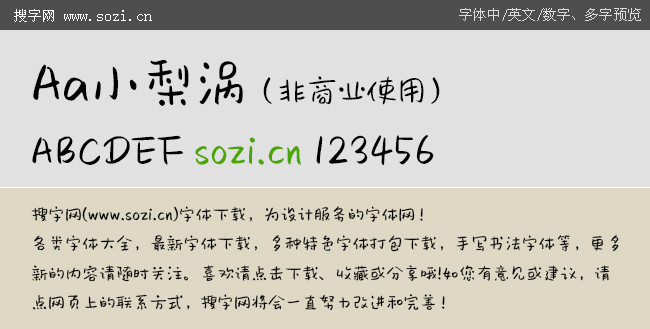
Aa小梨渦(非商業(yè)使用)
搜字網(wǎng)給大家提供一款A(yù)a小梨渦(非商業(yè)使用)中文字體下載,該字體是一款手寫風(fēng)格的卡通字體,充滿童趣,適合包裝畫冊(cè)等兒童卡通宣傳廣告等應(yīng)用(此字體為個(gè)人非商用版,商用可以聯(lián)系QQ:1006760504)。